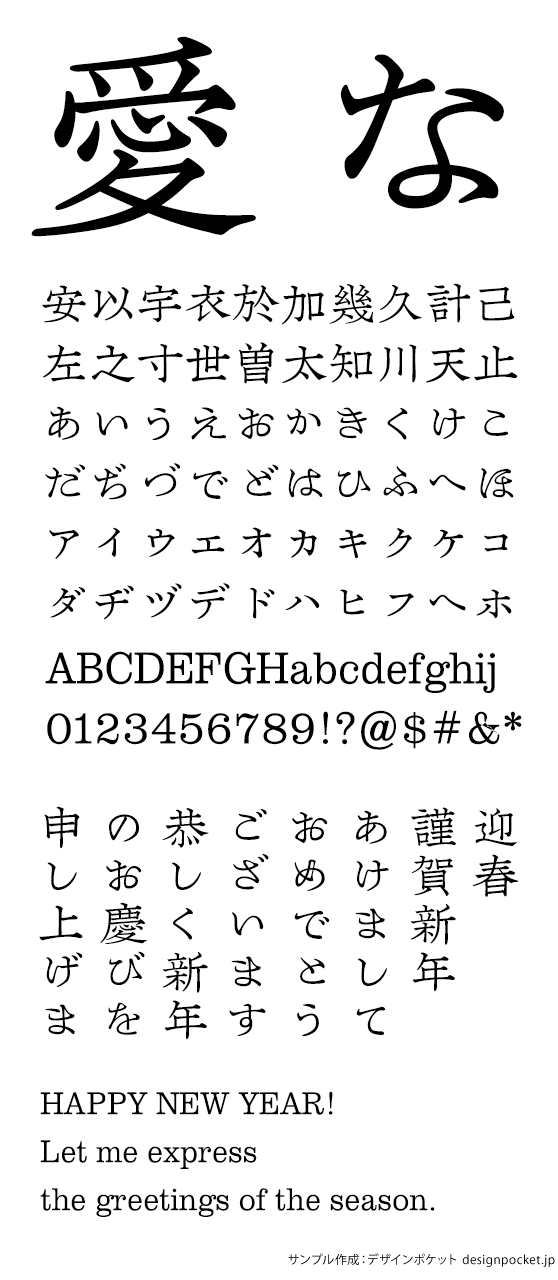
アンチック体
KOたまゆら方広M
KOTamayuraHoko-M
『言海』(大槻文彦著、六合館、1931)の見出し語から復刻した和字アンチック体「たまゆら」に、北宋代の仏教経典『大方廣佛華巖経』(龍興寺、990–994)にもちいられた字様をもとに翻刻した中世安竹体「方広」、ロバート・ベズリによる「クラレンドン」が掲載されている『印刷活字総合見本帳』(ファン・ストリート活字鋳造所、1857年)所収の見本から復刻したスラブセリフ体「K.E.Pisces」を組み合わせたKOたまゆら方広BKのファミリーで、メディウム・ウエイトです。